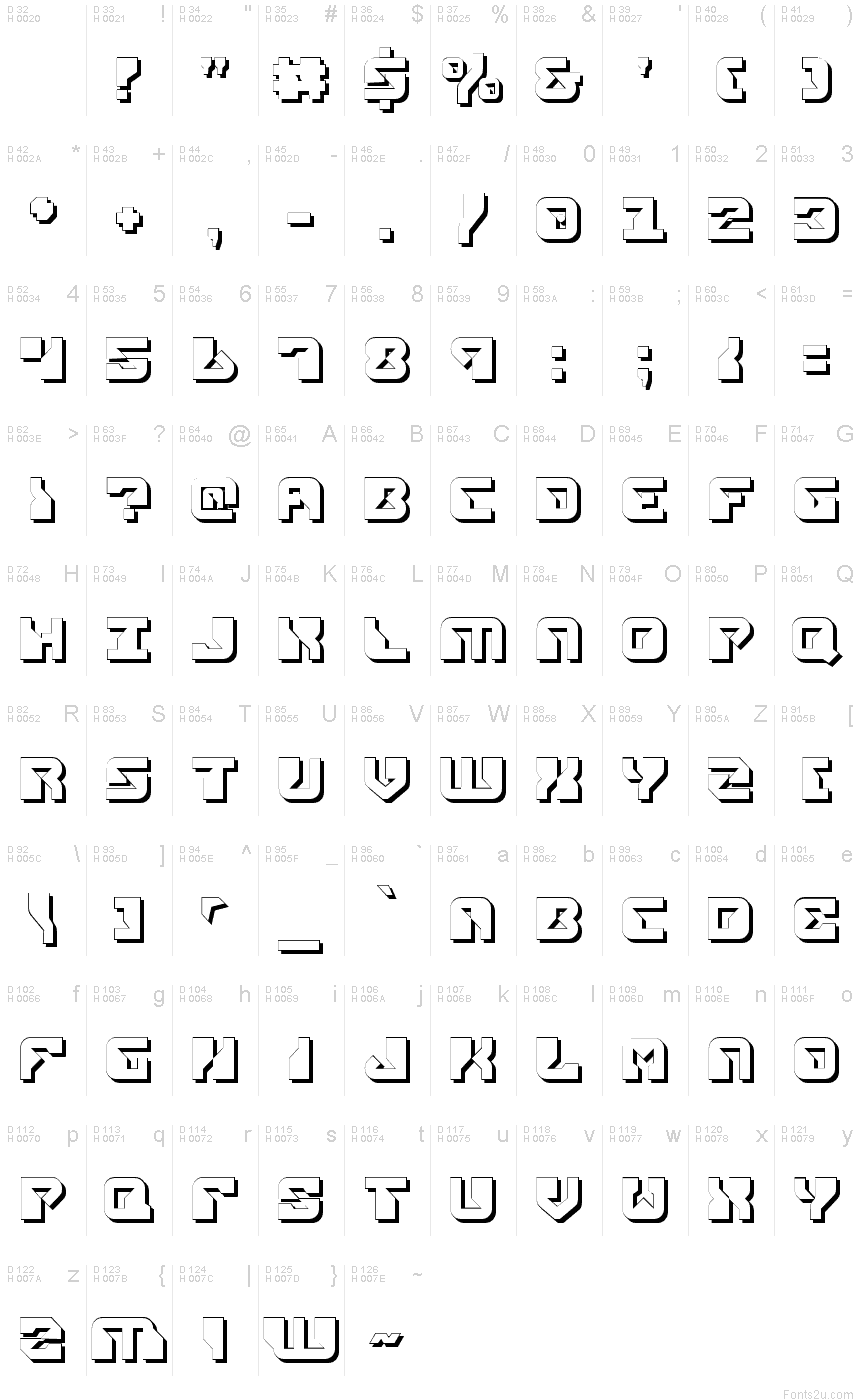
Replicant Shadow de Iconian Fonts es una tipografía display futurista y gratuita, con el estilo cortante de los títulos de ciencia ficción. Sus letras se basan en formas geométricas sólidas, acentuadas por cortes diagonales afilados y una sombra desplazada profunda que le da al abecedario un toque mecánico, sintético y con un aire retro de consola.
Encaja de forma natural en titulares de carteles, flyers de eventos tecno, branding con estética arcade, tarjetas de título y portadas donde las palabras cortas necesitan una silueta audaz y diseñada. Al ser una tipografía gratuita, también funciona muy bien para logotipos y gráficos de interfaz, ya que esa sombra pesada aporta un efecto dimensional y de capas, incluso en composiciones sencillas en mayúsculas.
Replicant Shadow